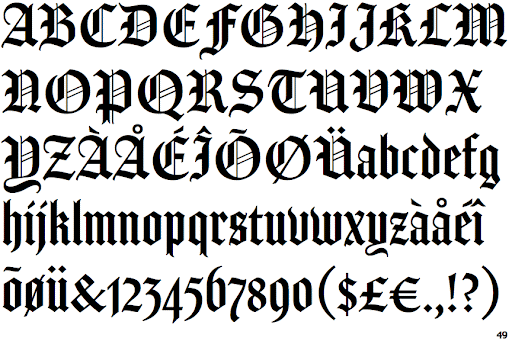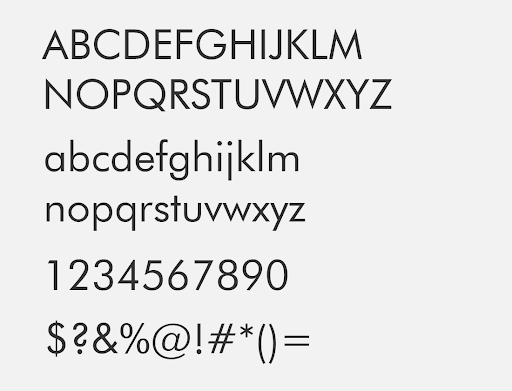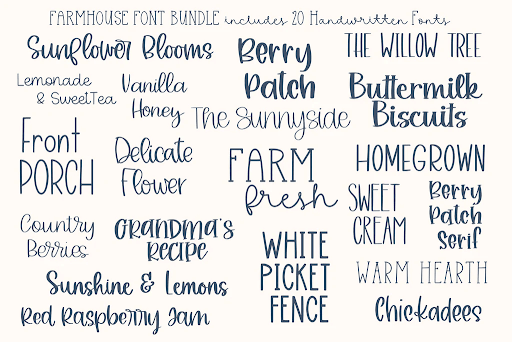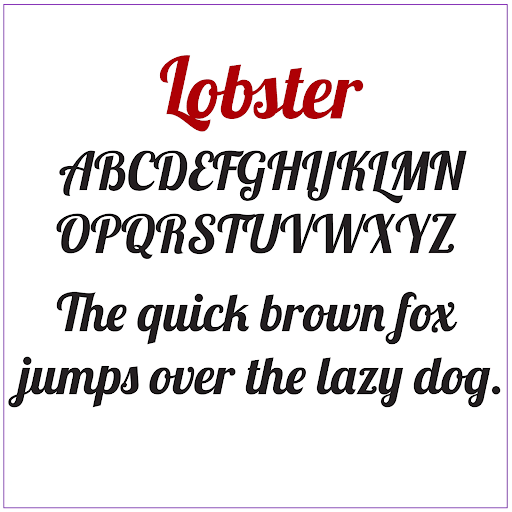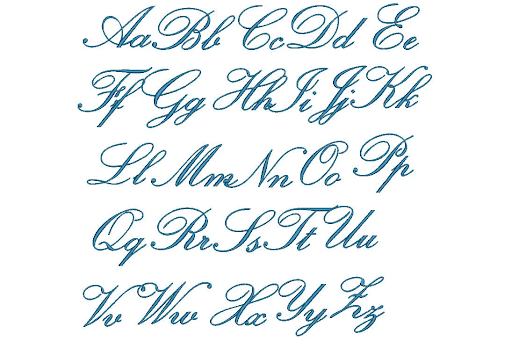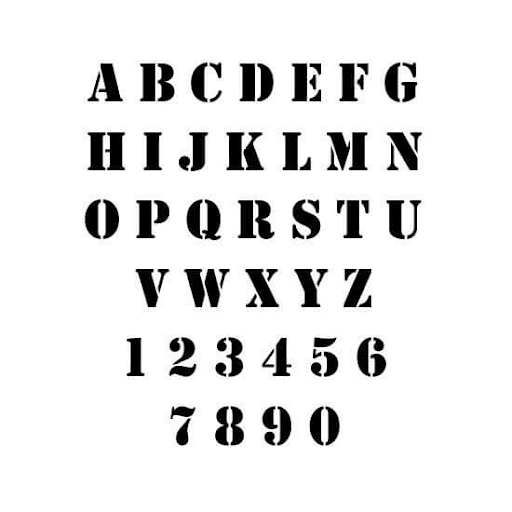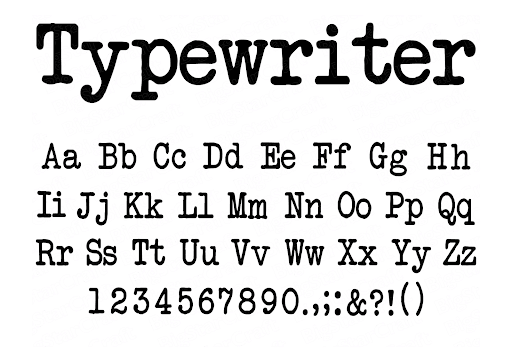
10+ Rekomendasi Font untuk Logo yang Bikin Brand Lebih Berkarakter
Pernah nggak sih kamu melihat sebuah logo, lalu langsung bisa menebak brand tersebut bergerak di bidang apa—padahal belum baca penjelasannya sama sekali? Nah, salah satu faktor terbesarnya adalah font.
Font yang tepat bisa membuat brand terlihat profesional, ramah, mewah, fun, atau bahkan menantang. Sebaliknya, font yang salah bisa bikin brand terasa nggak nyambung dengan produk atau target audiensnya. Untuk selengkapnya, yuk kita bahas lengkap di sini!
Kenapa Font Itu Penting dalam Logo?
Bayangkan sebuah brand kopi artisan menggunakan font yang kaku seperti font dokumen resmi. Rasanya pasti aneh, kan? Nah, makanya pemilihan font untuk logo itu penting.
Font dalam logo berfungsi untuk:
• Menyampaikan karakter brand (serius, santai, premium, playful, dan lainnya)
• Membangun kesan pertama di mata audiens
• Membantu brand lebih mudah diingat
• Menciptakan konsistensi visual di semua media termasuk pemilihan warna brand (kemasan, website, sosial media)
Macam-Macam Jenis Font dan Karakteristiknya
Sebelum masuk ke rekomendasi font, kamu perlu mengenal dulu jenis-jenis font utama dan kesan visual yang mereka bawa. Setiap jenis font punya kepribadian masing-masing, dan kepribadian inilah yang nantinya akan memengaruhi bagaimana brand kamu dipersepsikan oleh audiens.
Berikut jenis-jenis font yang bisa digunakan untuk logo:
1. Serif
Font serif adalah jenis font yang memiliki “kaki” atau garis kecil di ujung setiap hurufnya. Detail kecil ini membuat font serif terasa lebih rapi, berstruktur, dan berwibawa. Karena tampilannya yang klasik, serif sering diasosiasikan dengan brand yang ingin menunjukkan kredibilitas, kepercayaan, dan pengalaman panjang di bidangnya.
2. Sans Serif
Berbeda dengan serif, font sans serif tidak memiliki kaki pada ujung hurufnya. Tampilan inilah yang membuat sans serif terlihat lebih bersih, simpel, dan modern. Font jenis ini sangat populer di era digital karena mudah dibaca di layar dan terasa lebih relevan dengan gaya hidup masa kini.
3. Script
Font script meniru bentuk tulisan tangan atau kaligrafi, sehingga tampilannya terasa lebih mengalir dan artistik. Kesan yang ditampilkan biasanya elegan, personal, dan romantis.
Namun, penggunaan font script perlu ekstra hati-hati—terutama untuk logo—karena jika terlalu rumit, bisa mengurangi keterbacaan dan malah membingungkan audiens.
4. Handwritten
Sekilas mirip dengan script, tapi font handwritten cenderung lebih kasual dan bebas. Bentuk hurufnya tidak selalu rapi, justru itulah yang menjadi daya tariknya. Font ini memberikan kesan santai, friendly, seru, dan sangat natural.
5. Display
Font display dibuat khusus untuk menarik perhatian. Bentuknya biasanya unik, tebal, dan tidak konvensional, sehingga langsung mencuri fokus saat dilihat. Karakter font ini cenderung bold, eksperimental, dan eye-catching.
Namun, karena sifatnya yang sangat mencolok, font display sebaiknya digunakan secara terbatas agar tidak mengganggu keterbacaan logo secara keseluruhan.
6. Comic
Font comic memiliki bentuk huruf yang menyerupai tulisan komik atau tulisan tangan anak-anak. Garisnya cenderung bulat, tidak kaku, dan terlihat ekspresif. Kesan utama yang muncul dari font ini adalah fun, santai, dan tidak formal.
Font comic bikin brand lebih berkarakter karena menghadirkan kesan ramah dan approachable. Namun, karena sifatnya yang sangat kasual, font comic kurang cocok untuk brand yang ingin terlihat profesional atau premium.
7. Stencil
Font stencil terinspirasi dari huruf cetakan stensil yang biasanya dipakai pada peti kayu, peralatan militer, atau marking industri. Ciri khasnya adalah adanya potongan pada huruf yang membuat tampilannya tegas dan fungsional.
Font ini seperti menyampaikan pesan bahwa brand tersebut solid, siap kerja, dan tidak banyak basa-basi.
8. Blackletter
Blackletter adalah font klasik yang terinspirasi dari tulisan manuskrip abad pertengahan. Bentuk hurufnya tajam, detail, dan penuh ornamen, sehingga langsung memberi kesan historis dan tradisional.
Font blackletter bikin brand lebih berkarakter karena sangat kuat secara visual dan emosional. Sekali lihat, audiens langsung menangkap nuansa heritage, berani, dan eksklusif.
9. Typewriter
Font typewriter meniru tampilan huruf mesin tik lama, dengan jarak antar huruf yang konsisten dan bentuk yang sederhana. Kesan yang muncul biasanya retro, jujur, dan apa adanya.
10+ Rekomendasi Font untuk Logo yang Bikin Brand Lebih Berkarakter
Berikut rekomendasi font yang sering digunakan untuk logo dan punya karakter kuat:
1. Playfair Display
Playfair Display adalah font serif dengan kontras tinggi antara garis tebal dan tipis, sehingga langsung memunculkan kesan elegan dan editorial. Karakter ini membuat brand terlihat berkelas, matang, dan penuh rasa percaya diri.